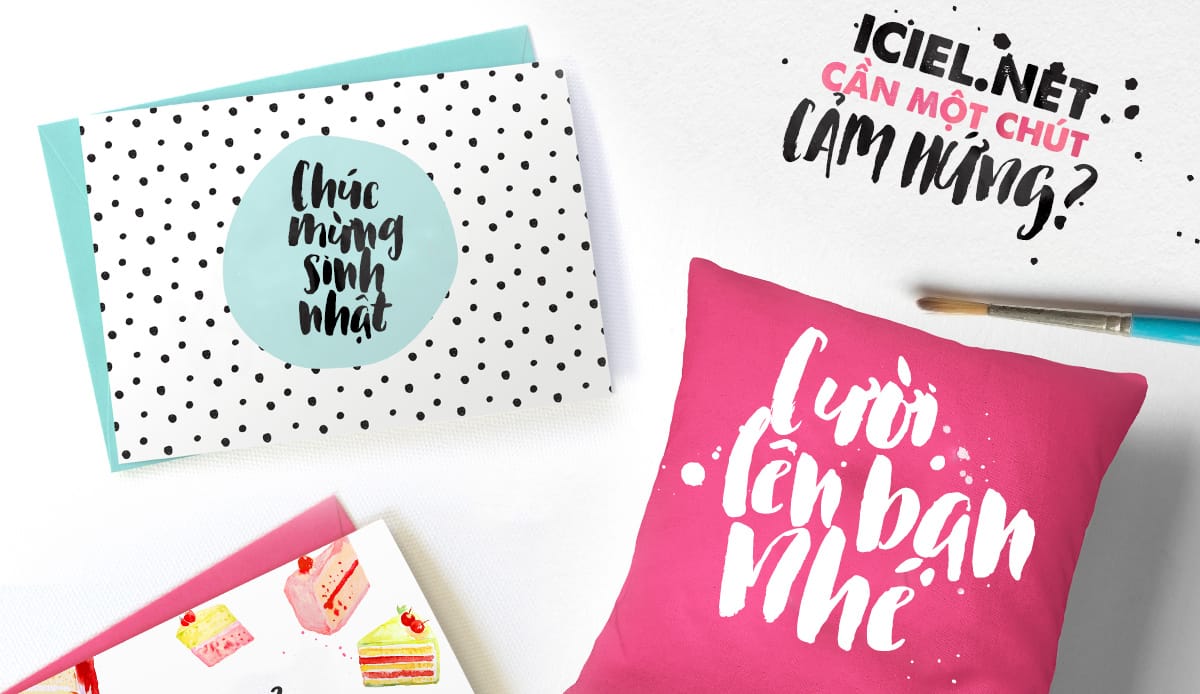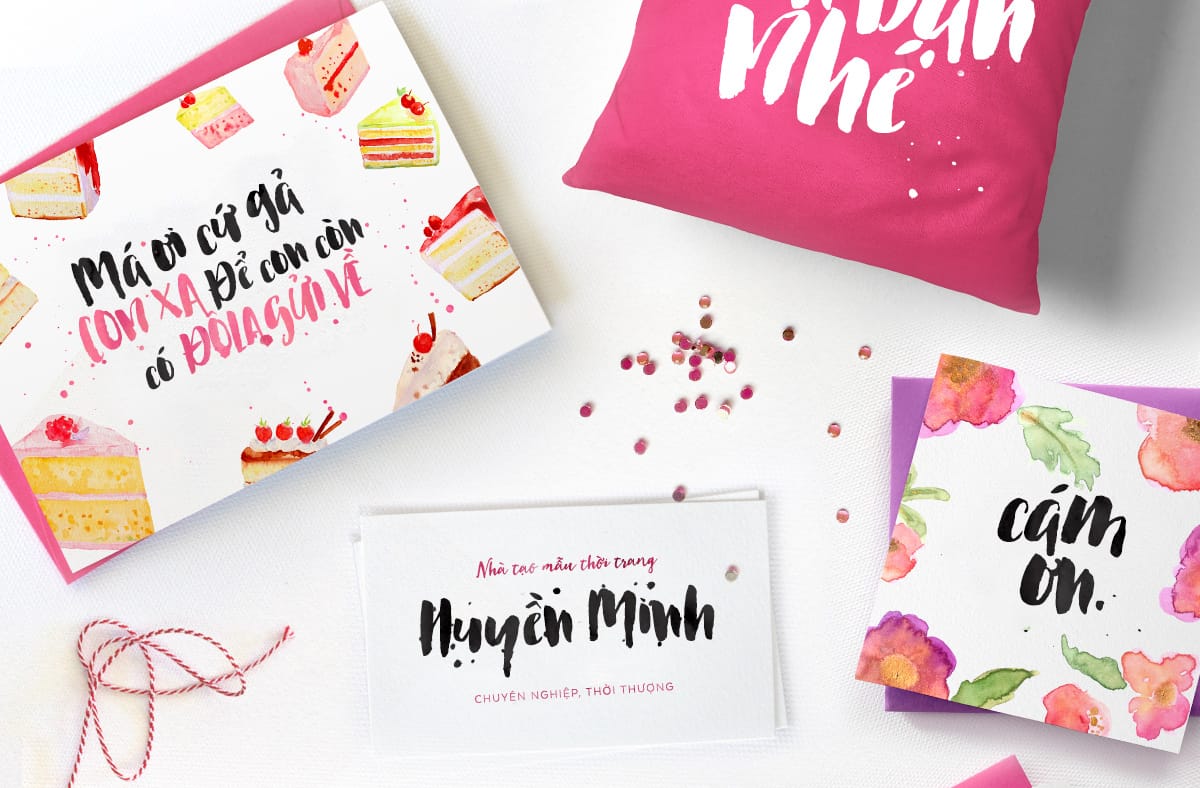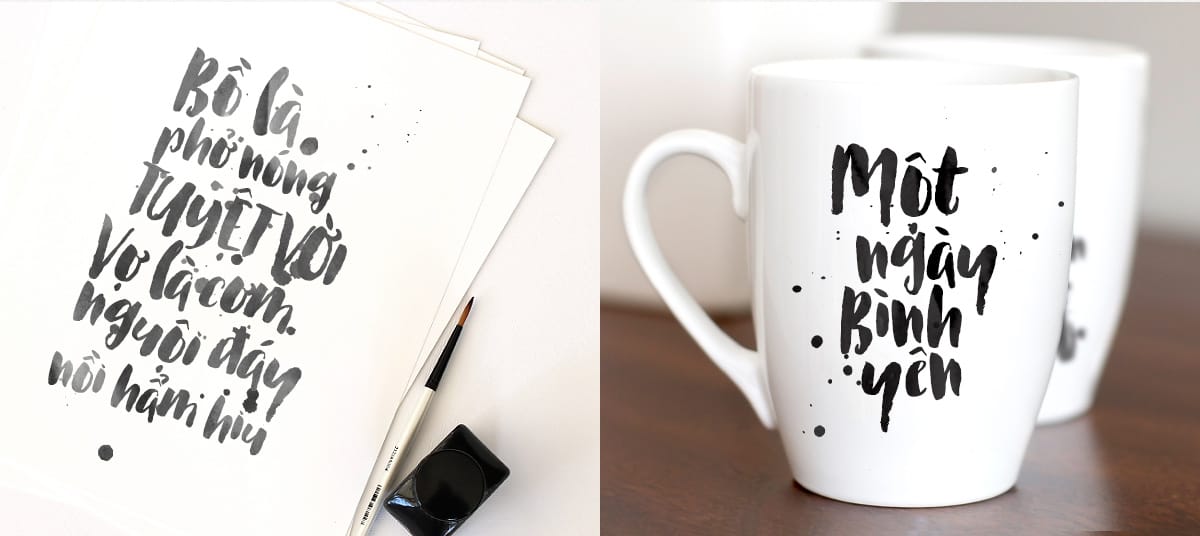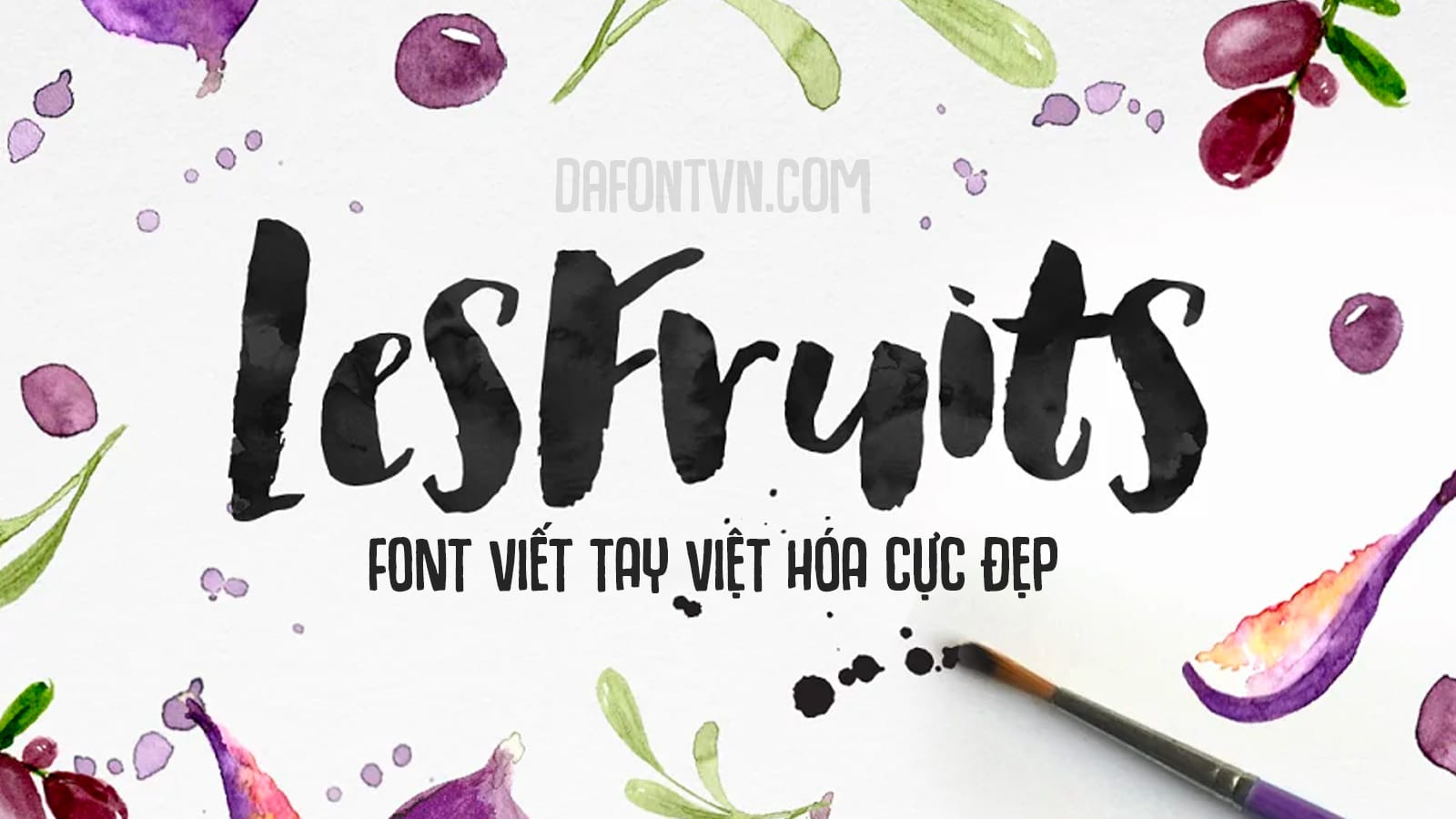
Font Les Fruits Brush Việt hóa một typeface sử dụng phong cách màu nước khá đẹp. Một phông chữ lấy cảm hứng từ những nét vẽ bằng bút lông. Phù hợp cho các thiết kế dựa trên mực hoặc màu nước như thiệp, thiết kế văn phòng phẩm, thư mời, áo phông, áp phích…Font còn đi kèm các tài nguyên với 5 vết mực nước loang, 10 style photoshop màu nước + 10 Equivalent Illustrator Swatches. Font được việt hóa bởi iCiel.